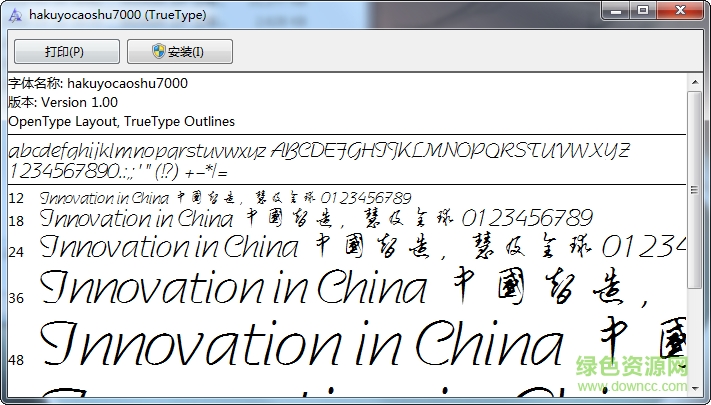
hakuyocaoshu7000
hakuyocaoshu7000又叫博洋草书7000字体,字体线条飞舞,笔墨张扬,奔逸洒脱,非常有艺术美,一般用在广告设计、艺术设计、古籍图书等方面,需要的朋友快来下载吧!
草书概念介绍
广义的草书是指草写的书体。它包括两种情况:
一是在文字不统一的远古时代,自然不会有统一规范的草书,那时出现的潦草的字,就属于广义的草书;
hakuyocaoshu7000字体
二是在文字统一后,在应急的情况下,或者是在起草文书稿件、记录他人谈话时,行笔快捷,笔画连带、省略,信手写的不规范的潦草的字,这种潦草的字很难用于交流,隔久了甚至连写字的人也难以识别,这种潦草的字就属于广义的草书。